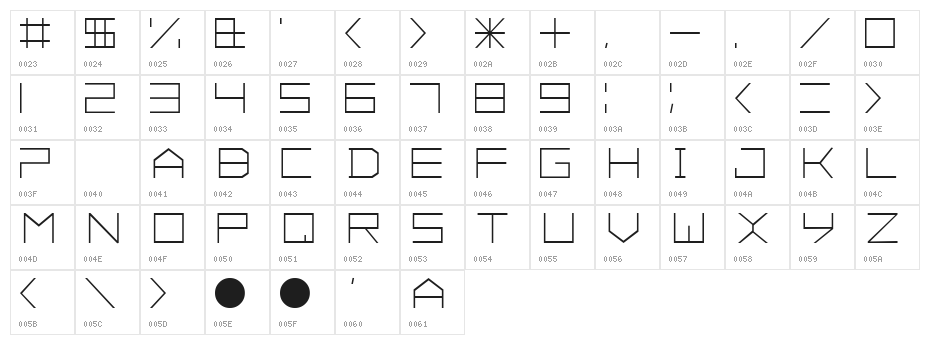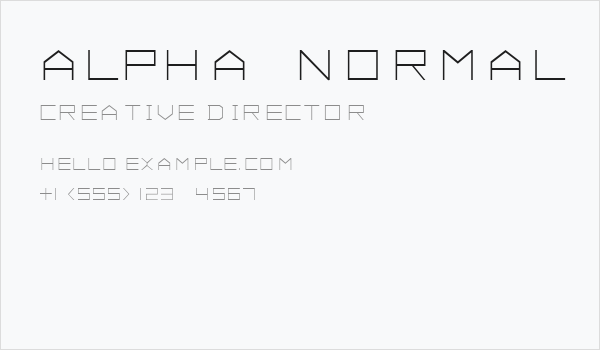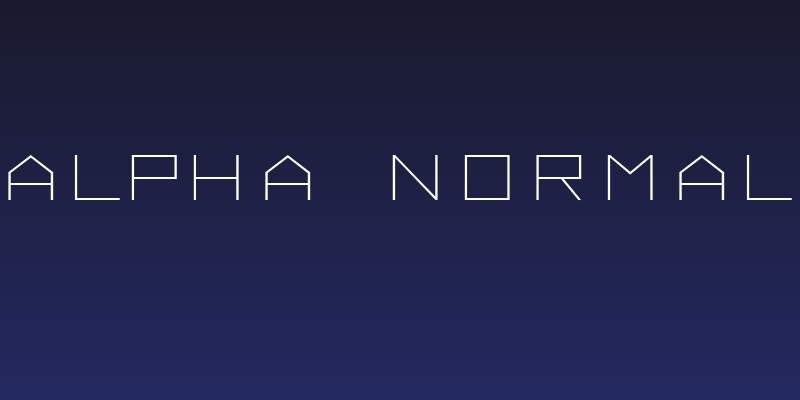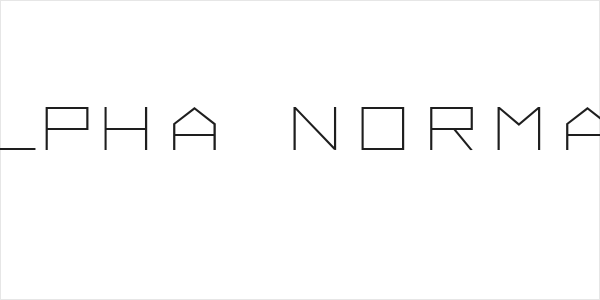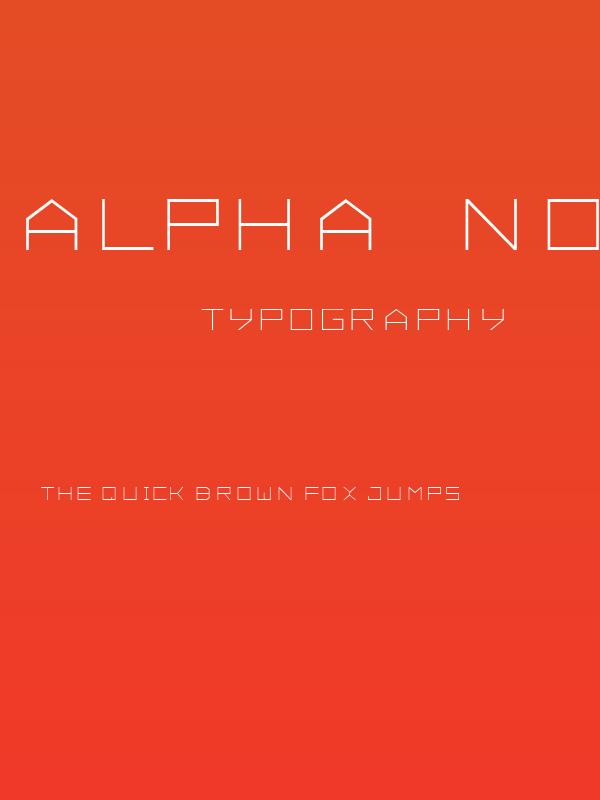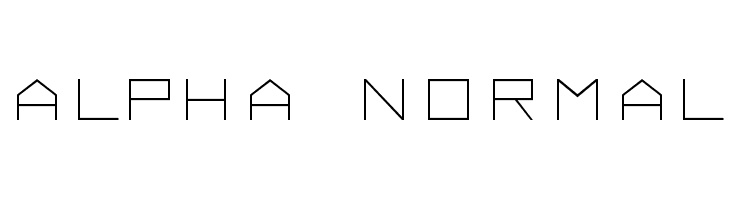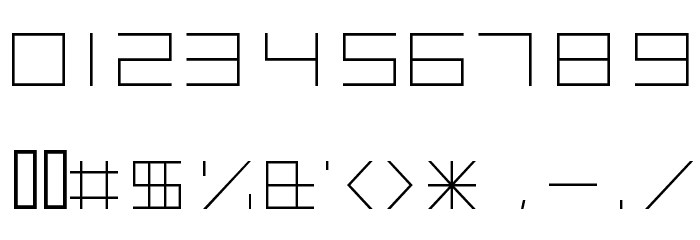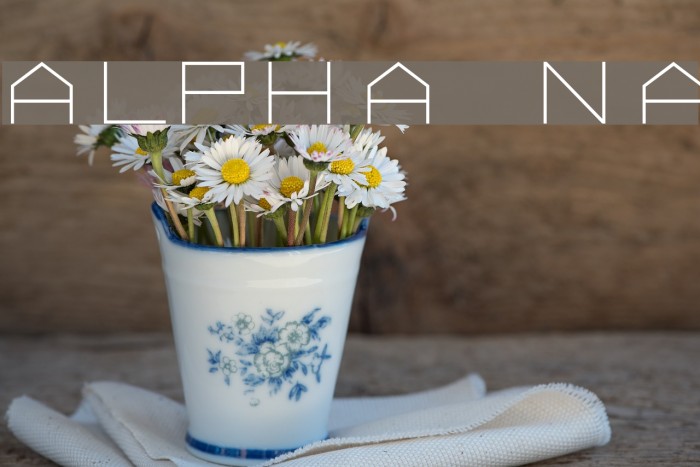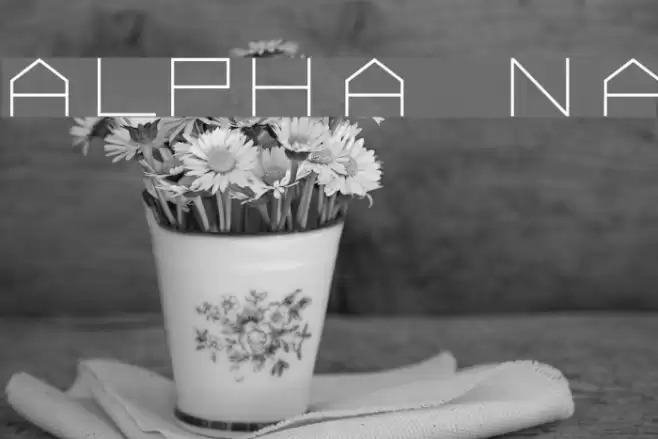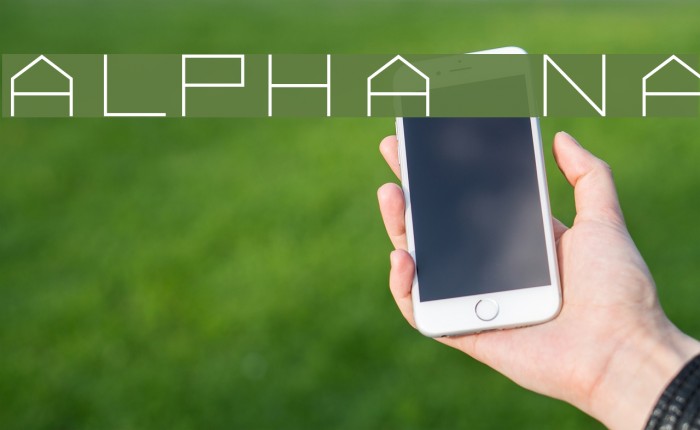
ALPHA Normal Font
| 用途 | Headlines, Logos, Digital interfaces |
| おすすめプロジェクト | Ideal for tech branding, modern posters, digital interfaces, and minimalist design projects. |